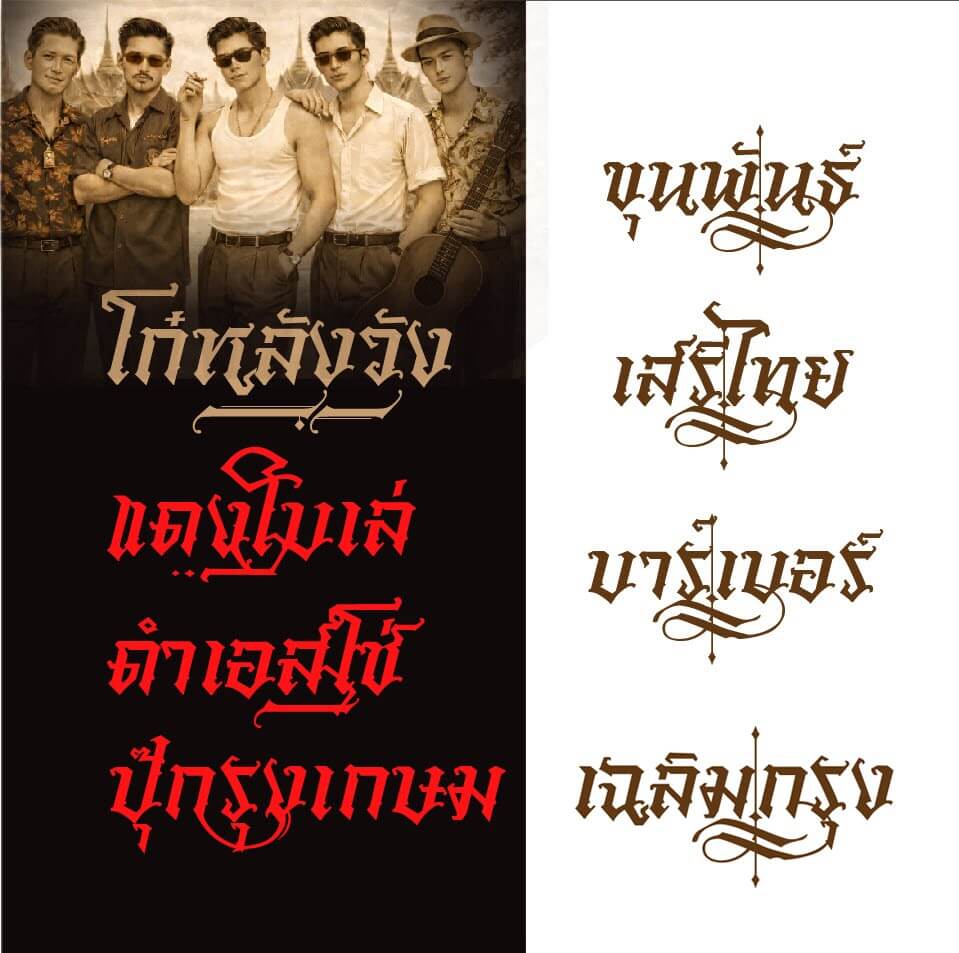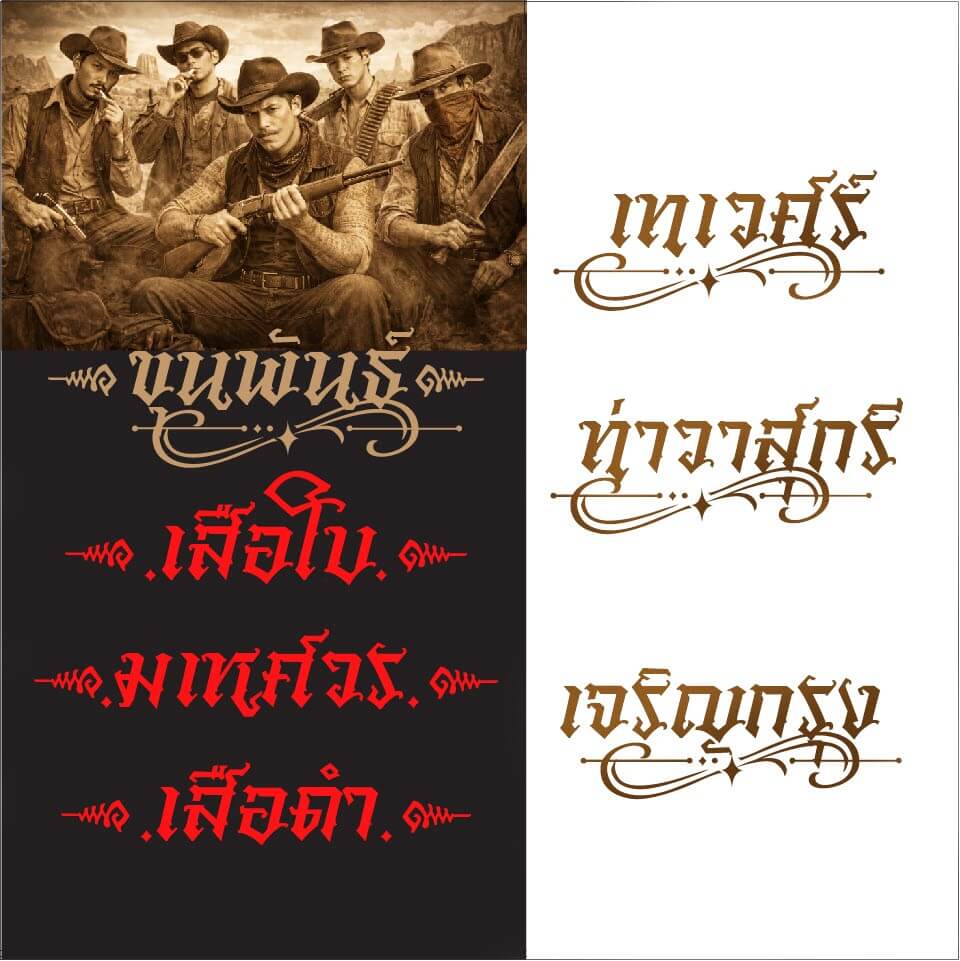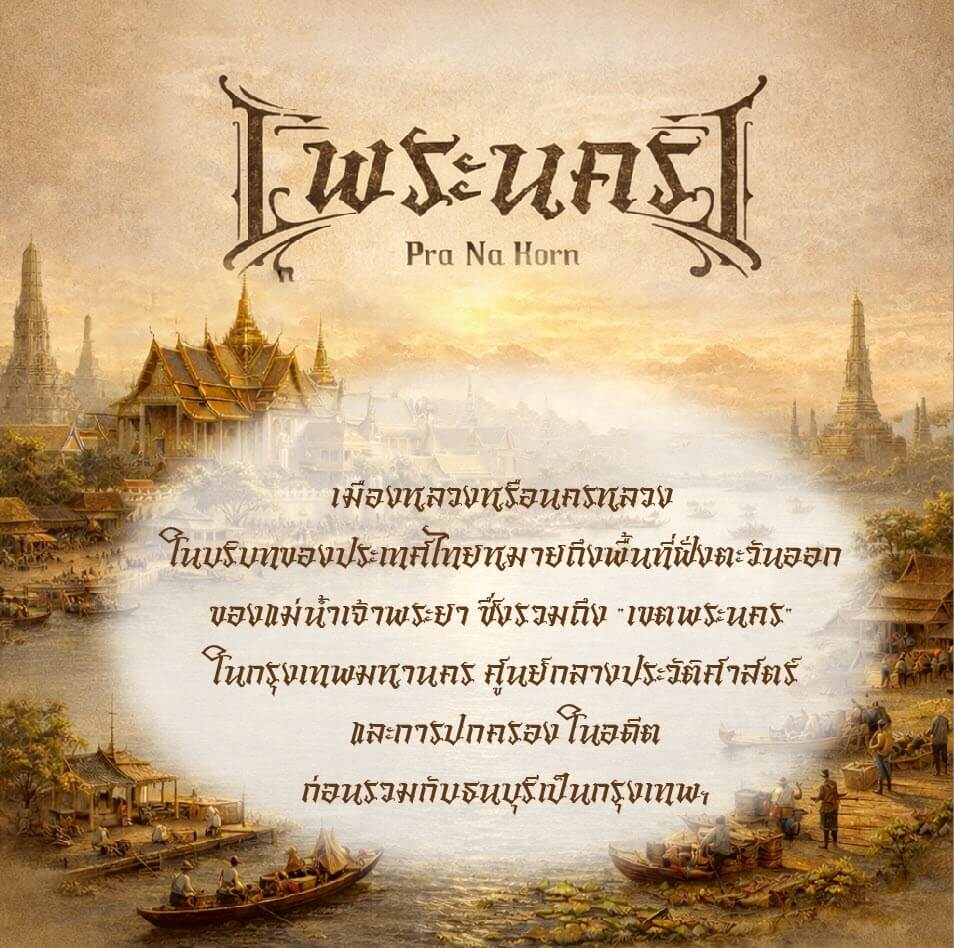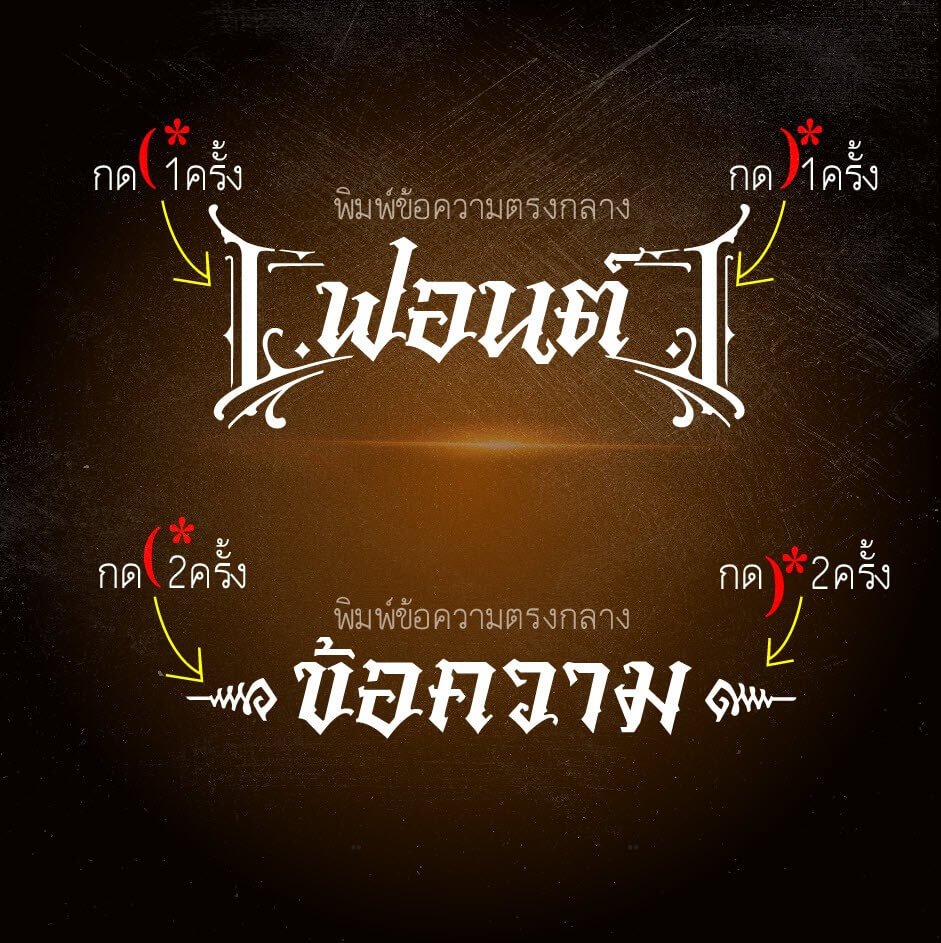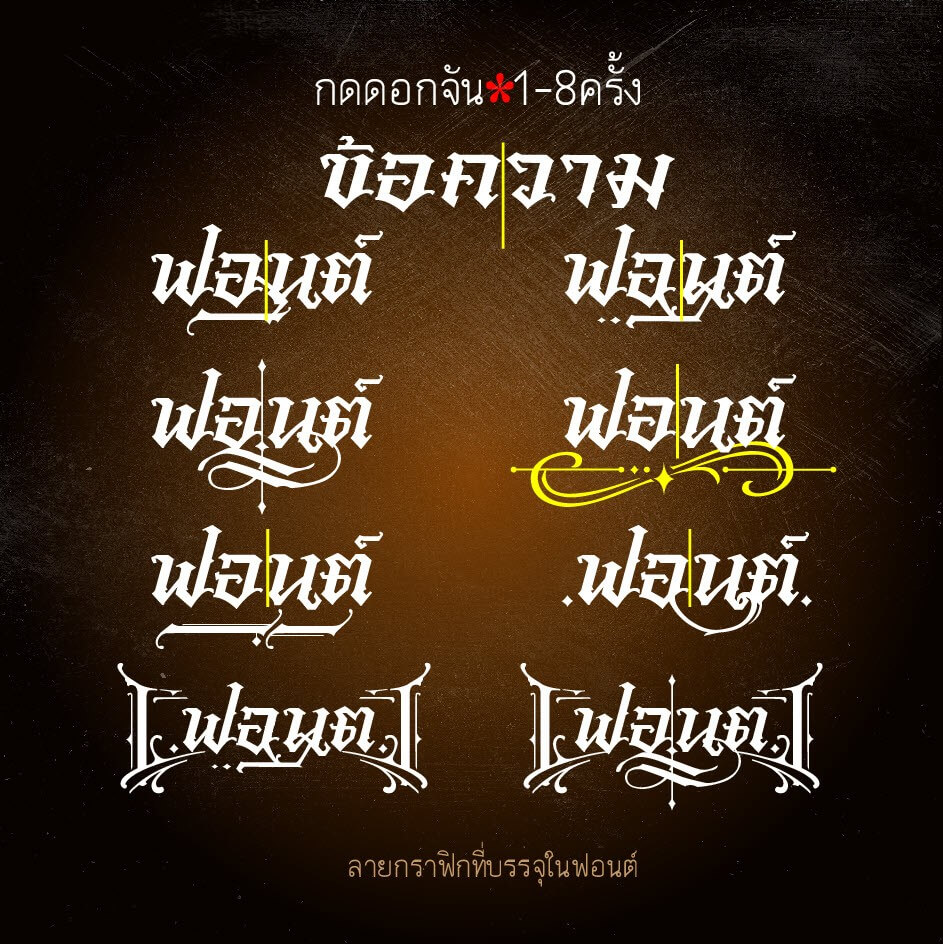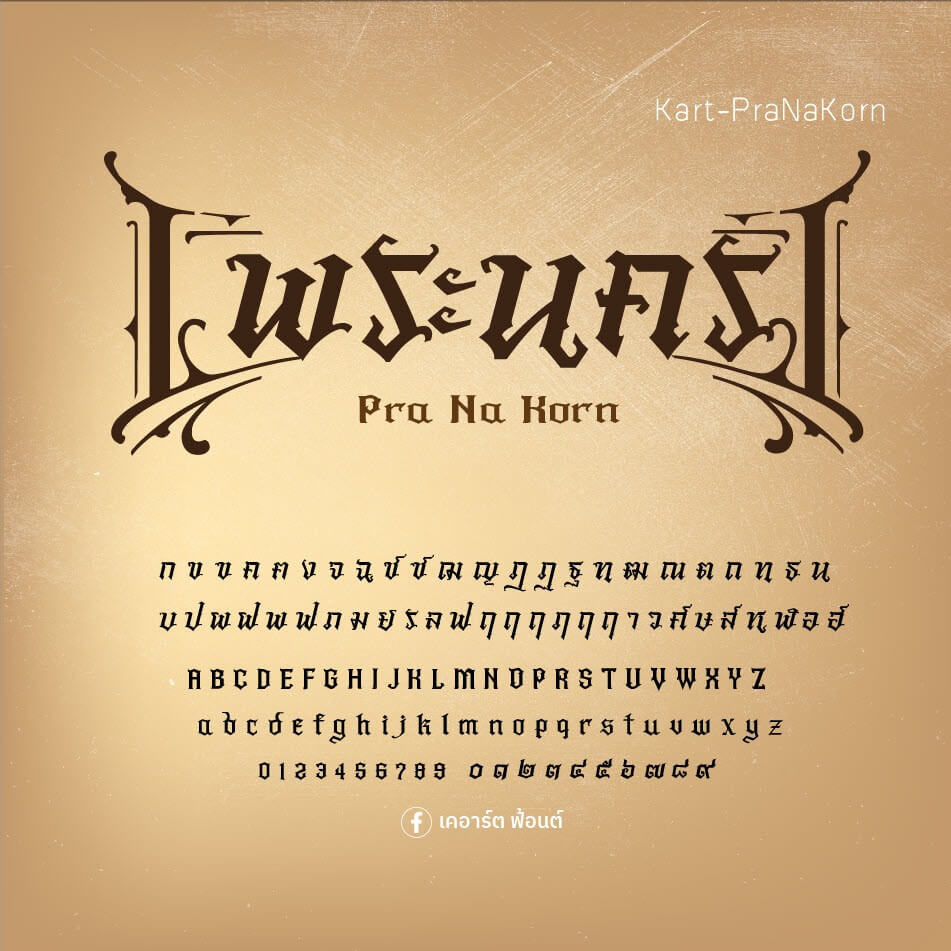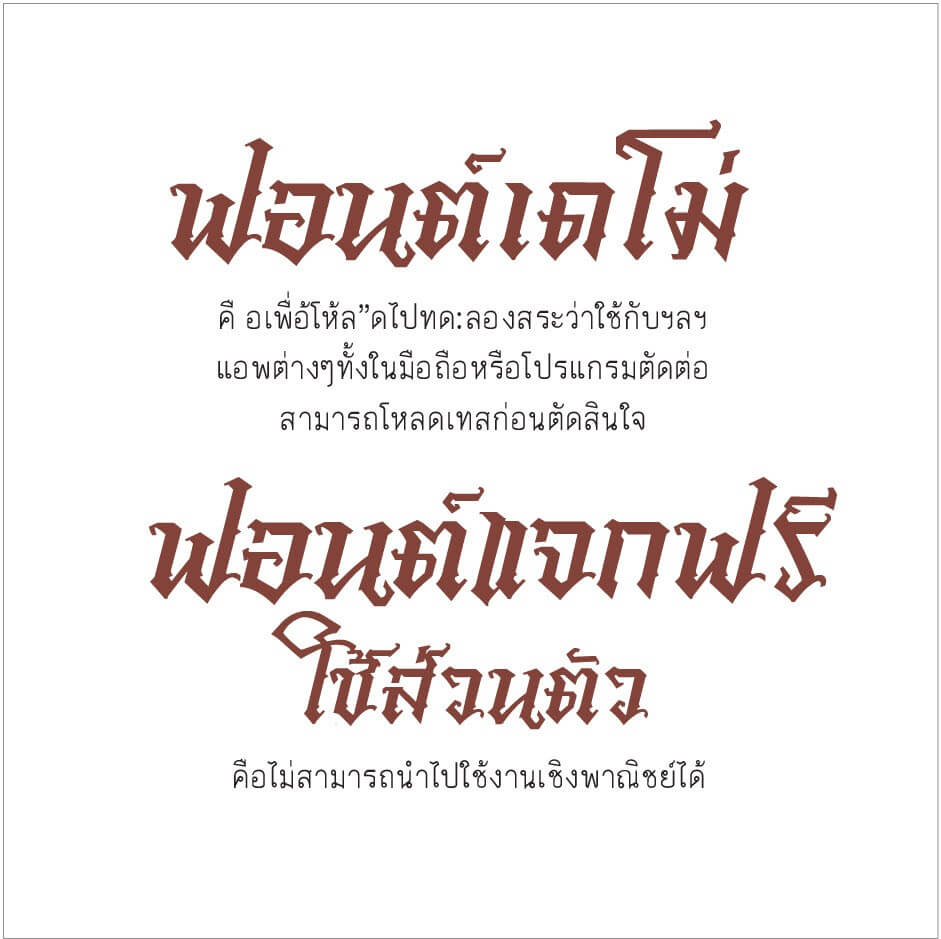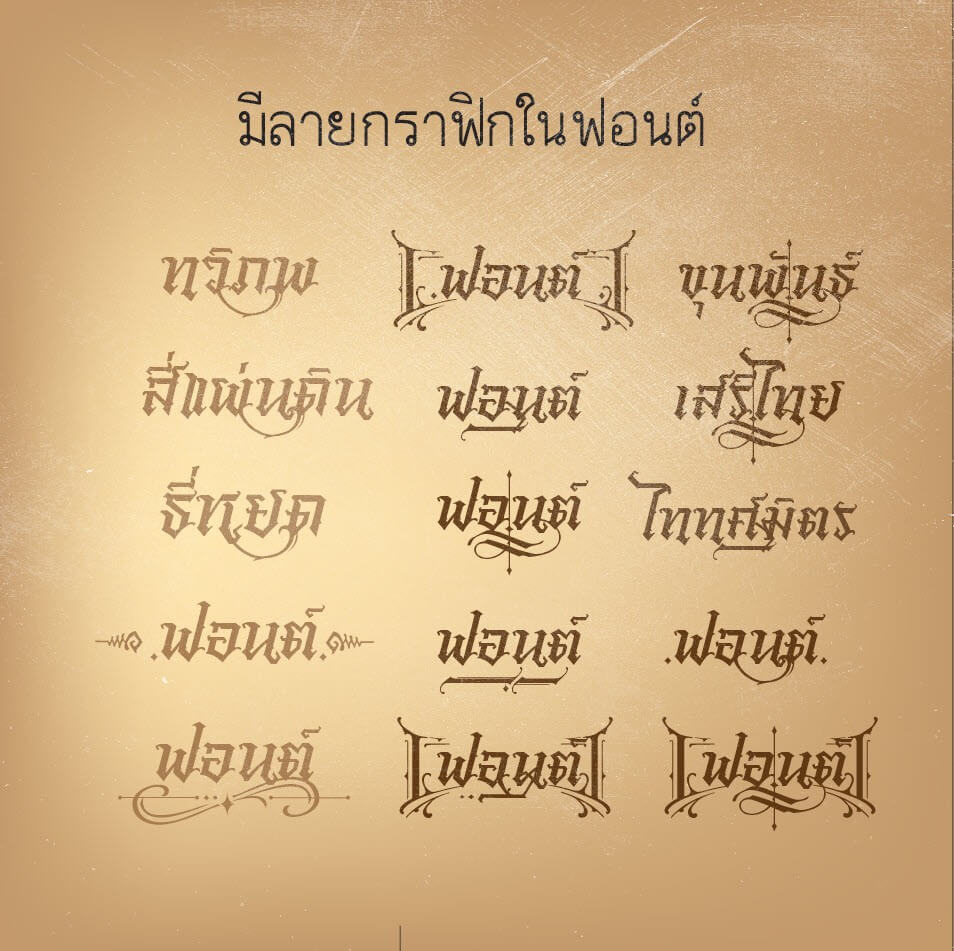
เคอาร์ต-พระนคร (Kart-PranaKorn)
ฟอนต์ เคอาร์ต-พระนคร (Kart-PranaKorn) – เป็นฟอนต์ที่เขียนอยากให้เป็น #ฟอนต์ย้อนยุค #ฟอนต์ไทยวินเทจ ย้อนยุค แบบสมัยก่อน ฟอนต์นี้มีลายกราฟิกอยู่ในฟอนต์ครับ
สร้างสรรค์โดย : เคอาร์ตฟอนต์